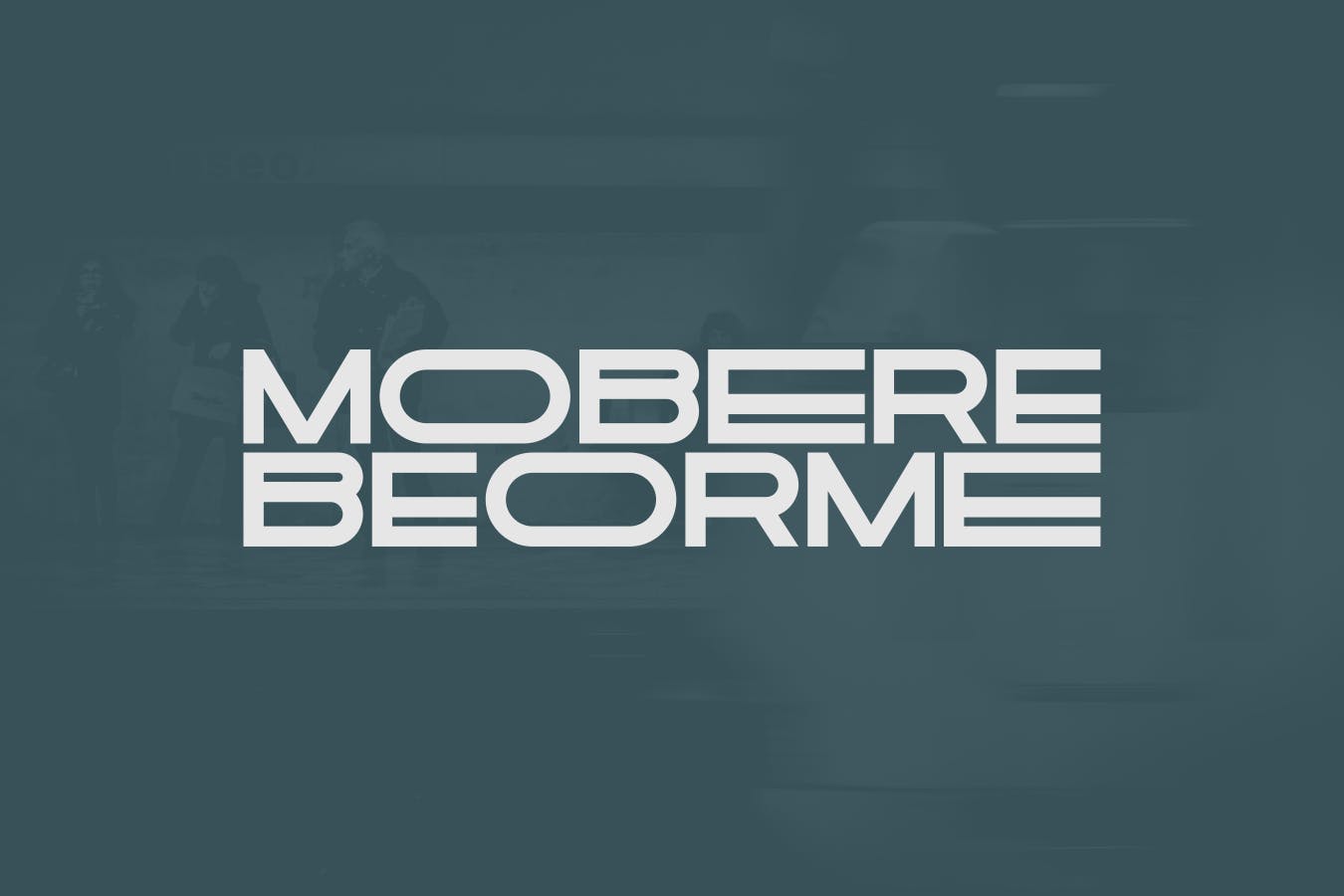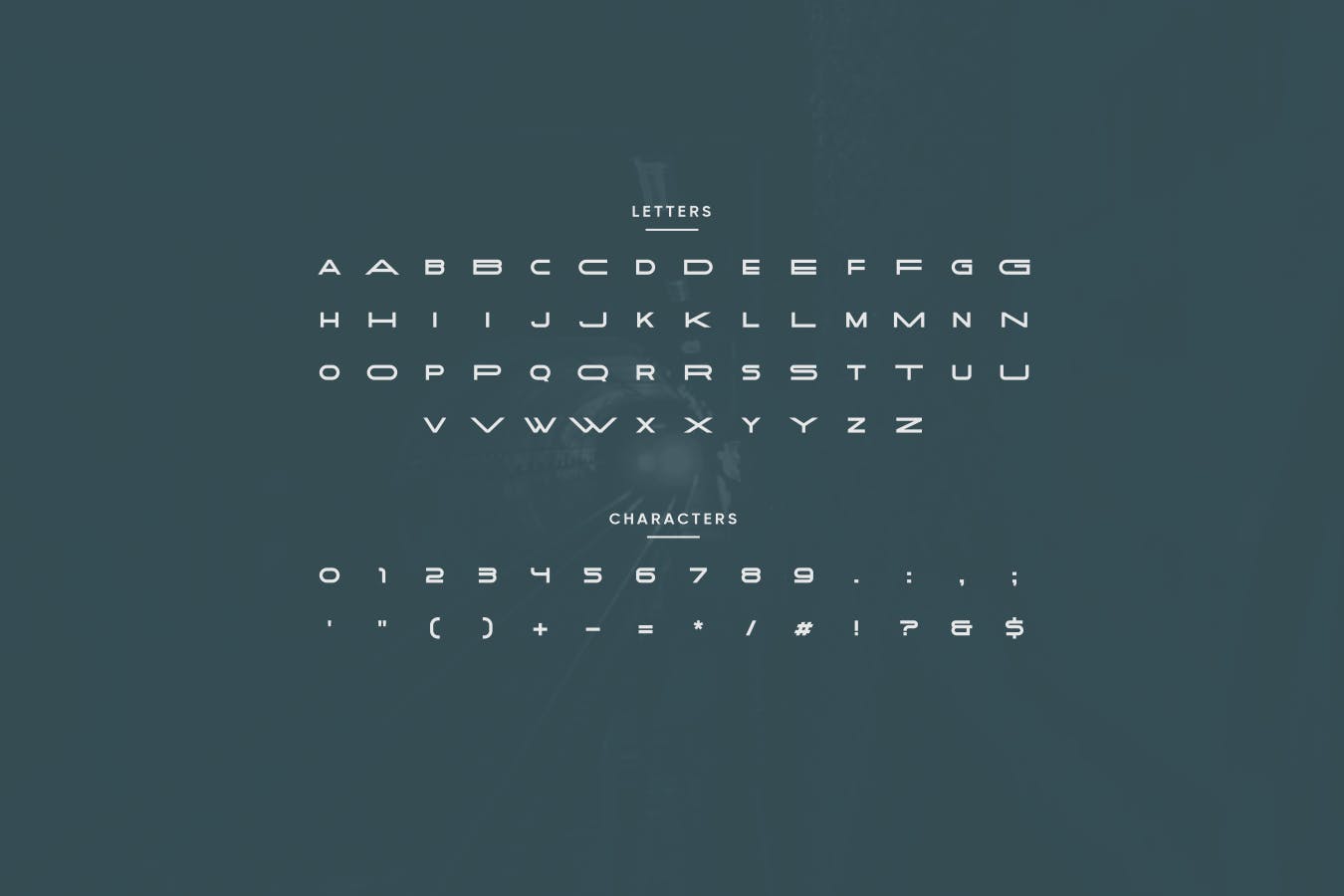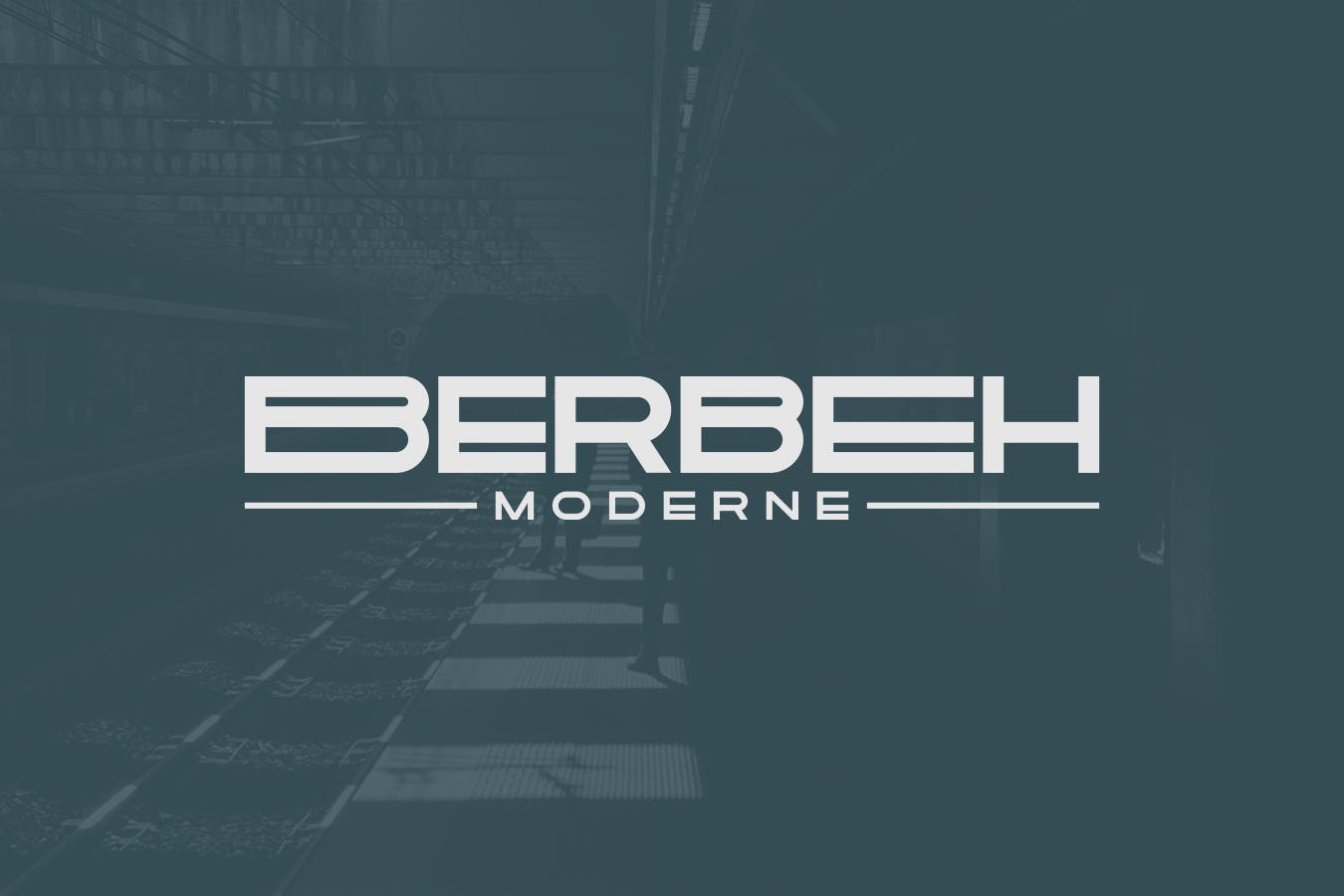
فونت Behmer یک فونت نمایشی با سبکی خاص است که در حالت حروف بزرگ کمی نوآوری دارد. این فونت با اینکه تمام حروف آن بزرگ است، اما سایز منحصر به فردی برای حروف کوچک دارد. این فونت برای هر چیزی که به آینده، تصویرسازی، پوستر، عنوان، لوگو، مجله و یا طراحیهای متنوع مربوط میشود، ایدهآل است و تجربهای متفاوت و برجسته را در طراحیهای شما به ارمغان میآورد.